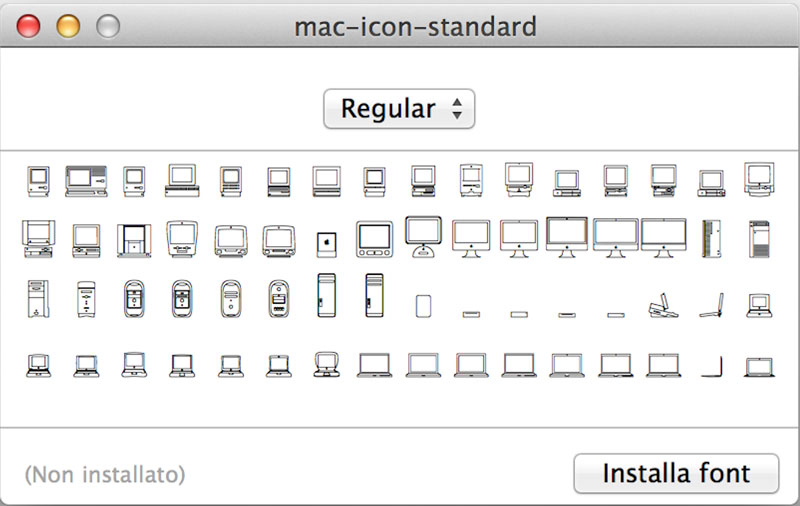
In occasione dei 30 anni dalla presentazione del primo Macintosh, Apple ha creato un mini-sito con una timeline di tutti i Mac e le testimonianze di utenti famosi che li hanno utilizzati. Per l’occasione, Cupertino ha realizzato perfino uno speciale font dei vari modelli di Mac.
Da MacUpdate, il noto sito che tiene traccia di tutti i software per la piattaforma Mac e non solo, è possibile scaricare gratuitamente 30 Years of Mac Font 1.000. Si tratta proprio del font OpenType TrueType utilizzato da Apple per la pagina celebrativa del trentennale del Macintosh, che contiene sessantaquattro caratteri, ma invece delle lettere ci sono i disegni stilizzati di ciascuno dei modelli che Apple ha prodotto dal 1984 ad oggi.